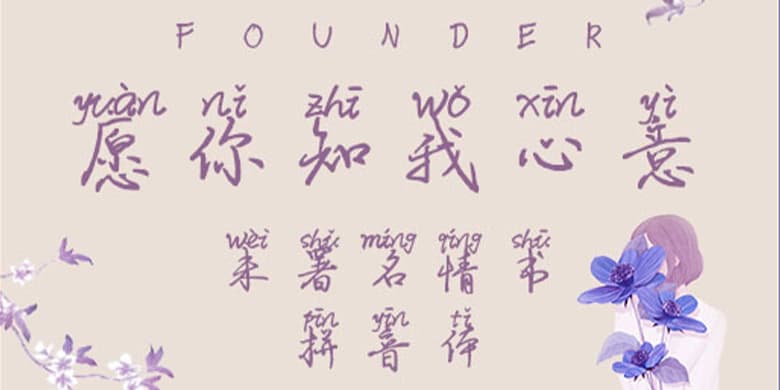
方正手迹-未署名情书拼音体
品牌:方正手迹设计师:林阳阳发行时间:2020字库编码:大陆简体(GB2312-80)分类:常规书写·硬笔字体属性:精品字
该字体行笔自然,转角圆润,从容不迫,结构严谨不呆板,起收笔间体现良好的书法功底。适用于文艺类的书刊、品牌广告和产品包装设计,以及社交网络的个性化用字。